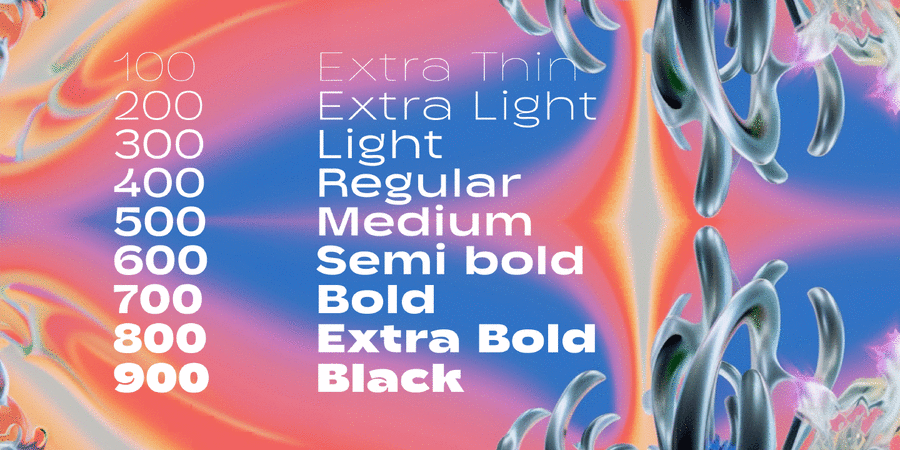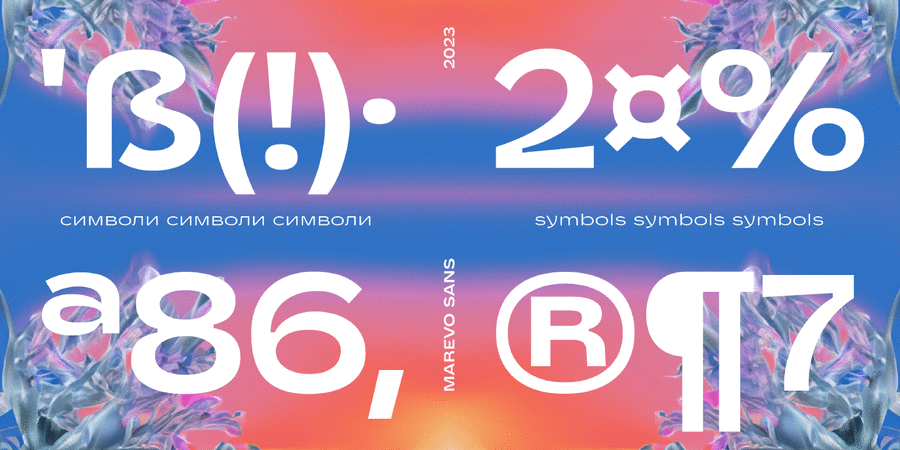
Marevo — сучасний гротеск з округлими, пухкенькими формами і великими чорнильними пастками. Шрифт підтримує кириличні та латинські символи, а також символи розширеної латинки. Має 9 накреслень від супер тонкого до блек. Марево має впевнений і, місцями, грайливий характер, що підійде для відкритих до експериментів та нових відкриттів бізнесів і брендів. Шрифт розробили Анастасія Шишенок і Кирило Ткачов у 2024 році.